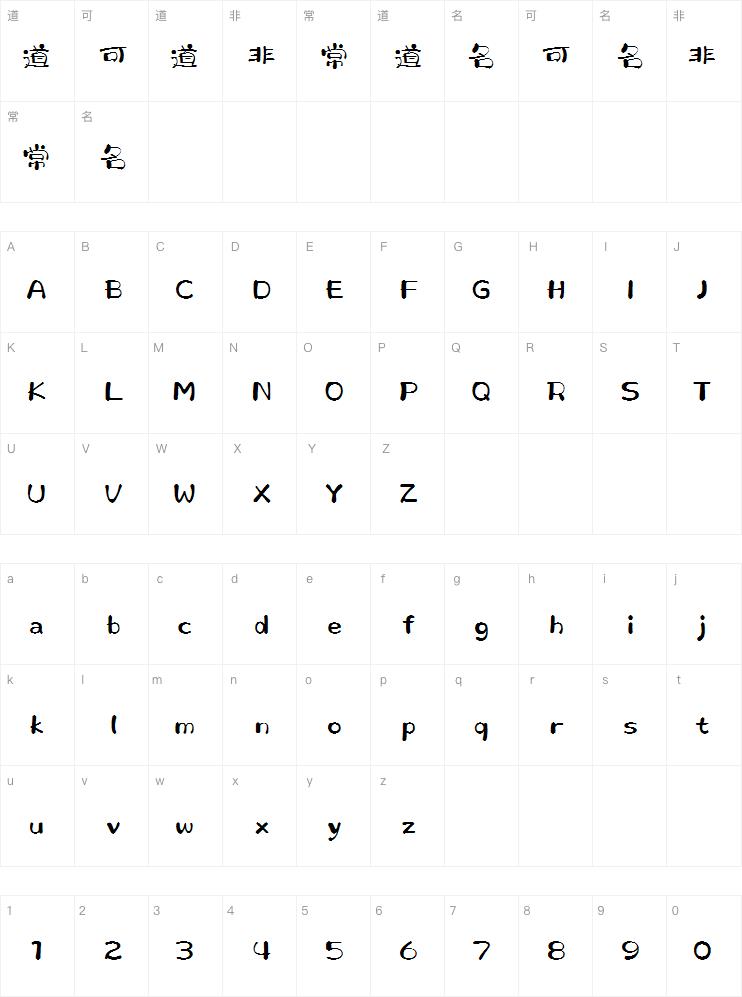
上首咿呀体,简体中文约6763字。这套字体笔画上,弱化了规整的提按转折,线条呈现出自然的顿挫与弧度,如孩童握笔时的稚拙运笔;字形结构打破常规字体的对称平衡,部分偏旁部首的大小、位置带有 “随意” 的偏移感,却在视觉上形成一种灵动的协调,恰似孩童书写时不受束缚的思维表达。字体整体保留了手写体的温度感,摒弃机械的规整,让每个字符都如咿呀学语的孩童笔迹般,充满天真烂漫的鲜活气息。